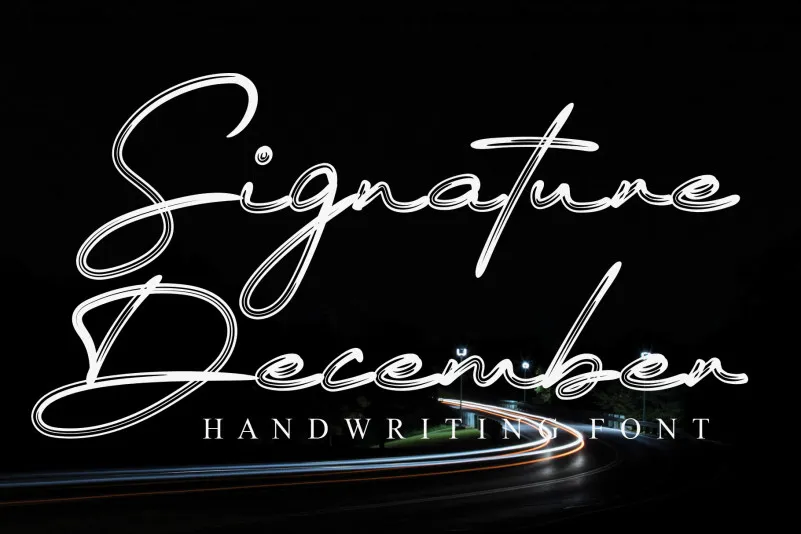
Signature December Script Font – Download Grátis
Signature December Script Font é uma linda fonte escrita a mão com traços cívilizados. Perfeita para adicionar um toque autêntico a cartões de véspera, cartões de agradecimento, citações e cartas de cumprimentos. Seus traços fluidos se destacam em cartazes de casamento, selos pessoais e identidades empresariais. Este design é uma ótima escolha para qualquer projeto que exige uma escrita humana, tornando-o um recurso indispensável para designers gráficos atentos ao detalhe. Ao usar a Signature December Script Font, você adicionará a sua peça de design aquele toque especial e autêntico.